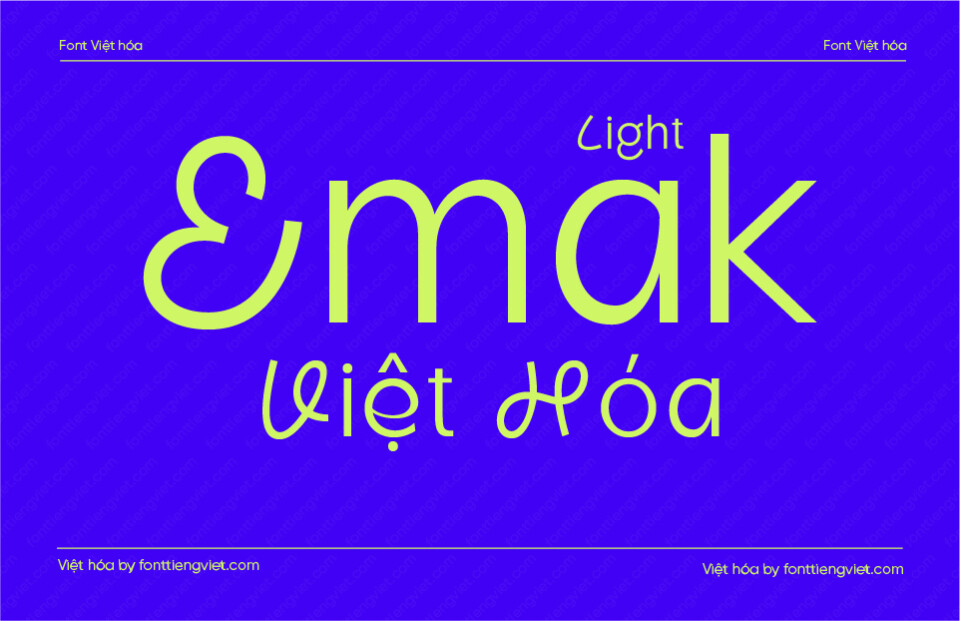
Font Việt hóa 1FTV VIP Emak Light – Font chữ thanh lịch cho thiết kế hiện đạiGiới thiệu về bộ Font Việt hóa 1FTV VIP Emak LightTrong thế giới đồ họa hiện nay, việc lựa chọn một bộ Font Miễn Phí chất lượng luôn là ưu tiên hàng đầu của các nhà thiết kế chuyên nghiệp lẫn người mới bắt đầu. Font Việt hóa 1FTV VIP Emak Light nổi lên như một giải pháp hoàn hảo cho những ai đang tìm kiếm sự tinh tế, thanh mảnh và hiện đại. Đây là phiên bản được tối ưu hóa đặc biệt, giúp người dùng tại Việt Nam có thể sử dụng trọn vẹn các ký tự tiếng Việt mà không lo bị lỗi hiển thị hay mất dấu. Với đường nét thanh thoát và bố cục cân đối, bộ font này mang lại cảm giác dễ chịu cho mắt người xem, đồng thời tạo nên vẻ ngoài chuyên nghiệp cho mọi tác phẩm nghệ thuật. Cho dù bạn đang làm việc trên các phần mềm như Photoshop, Illustrator hay Canva, bộ font này đều tương thích mượt mà và phát huy tối đa hiệu quả thẩm mỹ.Những đặc điểm nổi bật của Font Việt hóa 1FTV VIP Emak LightThiết kế thanh mảnh và tinh tếĐúng như tên gọi “Light”, bộ font này sở hữu những nét chữ mỏng manh nhưng vô cùng sắc nét. Cấu trúc của từng chữ cái được tính toán kỹ lưỡng để duy trì sự thông thoáng giữa các khoảng trắng, giúp văn bản trở nên thanh thoát hơn. Điều này cực kỳ hữu ích khi bạn cần trình bày các nội dung dài hoặc các đoạn trích dẫn ý nghĩa mà không muốn gây cảm giác nặng nề cho trang thiết kế.Khả năng ứng dụng đa dạng trong nhiều lĩnh vựcFont Việt hóa 1FTV VIP Emak Light không hề kén chọn bối cảnh sử dụng. Bạn có thể dễ dàng bắt gặp nó trong các thiết kế thiệp cưới sang trọng, bìa sách nghệ thuật, hoặc các ấn phẩm truyền thông cho ngành thời trang và làm đẹp. Đặc biệt, trong môi trường giáo dục, các bạn học sinh và giáo viên có thể dùng font chữ này để trang trí slide thuyết trình, làm báo tường hoặc thiết kế các chứng nhận khen thưởng nhờ vẻ ngoài trang nhã và lịch sự mà nó mang lại.Tối ưu hóa tiếng Việt hoàn chỉnhMột trong những điểm mạnh lớn nhất của phiên bản 1FTV VIP chính là việc xử lý dấu câu tiếng Việt cực kỳ chuẩn xác. Các dấu thanh như huyền, sắc, hỏi, ngã, nặng được đặt ở vị trí hợp lý, không bị quá cao hay quá thấp so với chữ cái chính. Điều này giúp bảo toàn tính thẩm mỹ tổng thể của câu văn, giúp thông điệp được truyền tải một cách trọn vẹn và chuyên nghiệp nhất đến độc giả.Hướng dẫn sử dụng và bảo quản Font Việt hóa 1FTV VIP Emak LightĐể tận dụng tối đa vẻ đẹp của bộ font này, bạn nên kết hợp nó với các tông màu trung tính hoặc pastel để tạo nên sự hài hòa. Việc sử dụng Font Việt hóa 1FTV VIP Emak Light cho các tiêu đề phụ hoặc nội dung chi tiết sẽ giúp phân cấp thông tin rõ ràng hơn trong bản thiết kế. Lưu ý rằng khi cài đặt, bạn chỉ cần giải nén tệp tin và cài đặt trực tiếp vào hệ thống máy tính để các ứng dụng soạn thảo văn bản và đồ họa tự động cập nhật. Đừng quên kiểm tra kỹ các định dạng tệp để đảm bảo font hiển thị tốt nhất trên cả màn hình kỹ thuật số và bản in ấn thực tế.Kết luận về bộ font chữ độc đáo nàyTóm lại, việc sở hữu một bộ font chữ đẹp và chuẩn kỹ thuật là chìa khóa để tạo nên những sản phẩm truyền thông ấn tượng. Hy vọng rằng qua bài viết này, bạn đã có cái nhìn chi tiết hơn về giá trị mà bộ chữ này mang lại cho cộng đồng sáng tạo. Hãy truy cập ngay tại Font Miễn Phí, Font Việt Hóa, Font Việt hóa 1FTV VIP Emak Light để tải về và bắt đầu trải nghiệm sự khác biệt. Đừng ngần ngại sáng tạo và biến những ý tưởng của mình thành hiện thực với sự hỗ trợ đắc lực từ Font Việt hóa 1FTV VIP Emak Light ngay hôm nay.
Font Việt hóa 1FTV VIP Emak Light